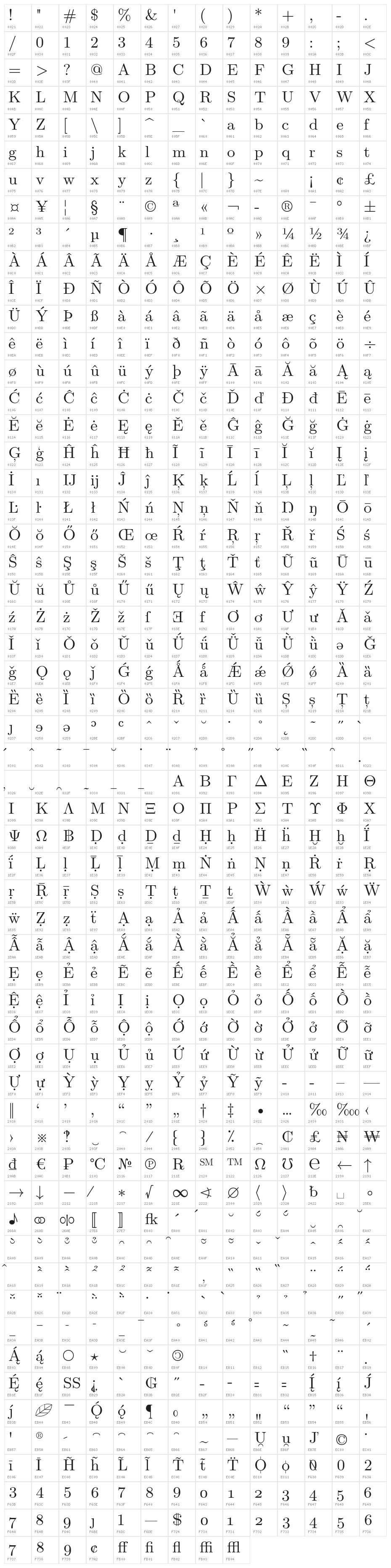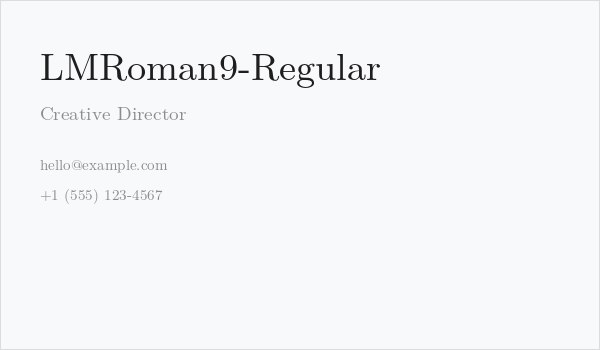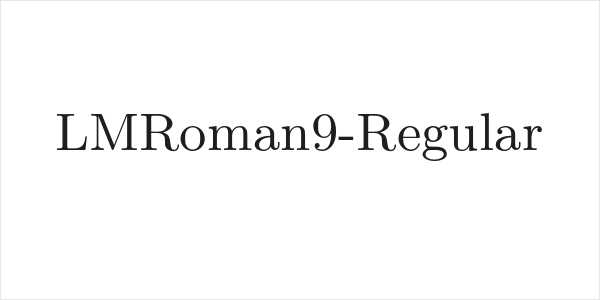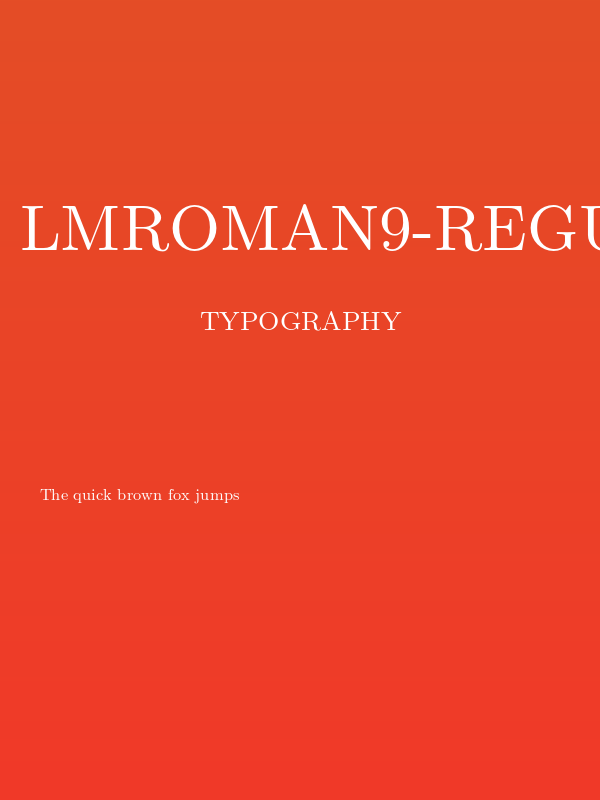
LMRoman9-Regular Font
✎ Serif
| Caso d'uso | Body text, Headlines, Print media |
| Progetti proposti | Ideal for book typesetting, formal invitations, academic publications, and corporate branding. |